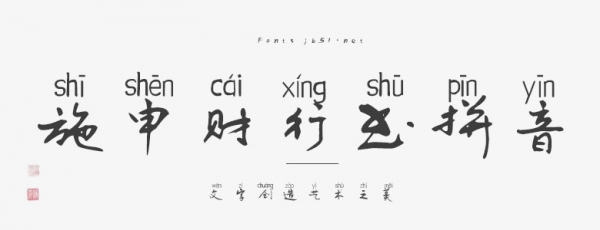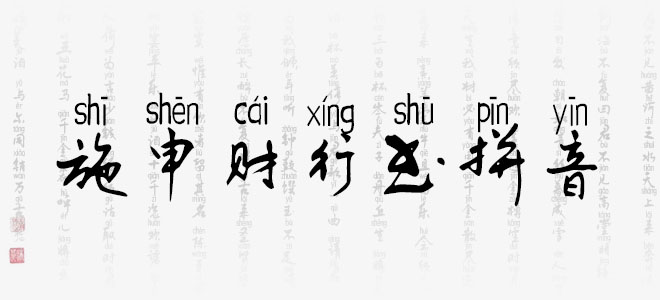
施申財(cái)行書(shū)拼音是一款書(shū)寫(xiě)很新穎的字體,自帶拼音標(biāo)注效果,具有強(qiáng)烈的視覺(jué)沖擊力。適用于海報(bào)、電商海報(bào)設(shè)計(jì)、店鋪設(shè)計(jì)、標(biāo)志設(shè)計(jì)、字體設(shè)計(jì)等領(lǐng)域。
施申財(cái)行書(shū)拼音